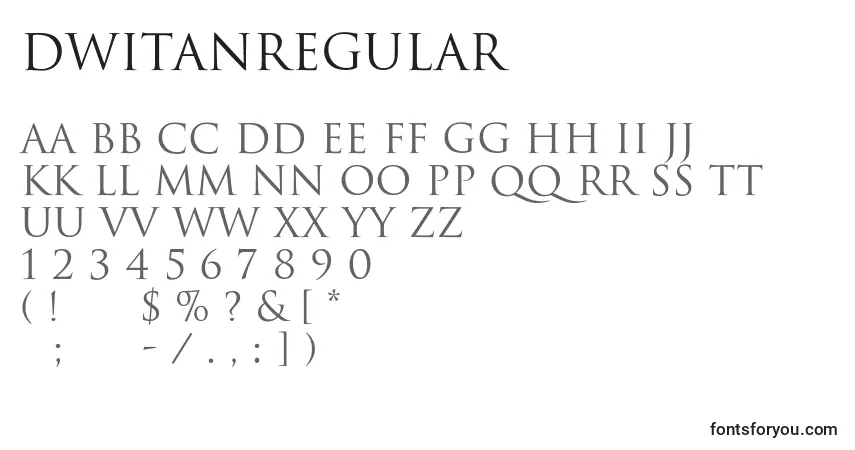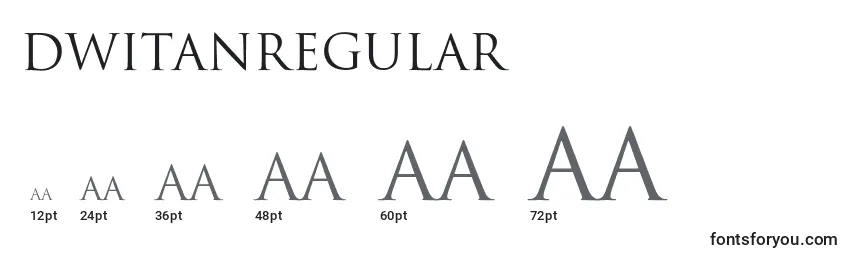
Police DwitanRegular
J'ai récemment découvert la police de caractères Dwitan Regular et je suis vraiment impressionné par sa beauté et son élégance. Les lignes épurées et les courbes douces donnent à chaque lettre une allure unique et moderne. De plus, la lisibilité est excellente, ce qui en fait un choix parfait pour les présentations professionnelles et les projets créatifs. Je suis tombé amoureux de cette police dès que je l'ai vue et je suis convaincu qu'elle apportera une touche de sophistication à n'importe quel design. Je suis impatient de l'utiliser dans mes prochains projets!